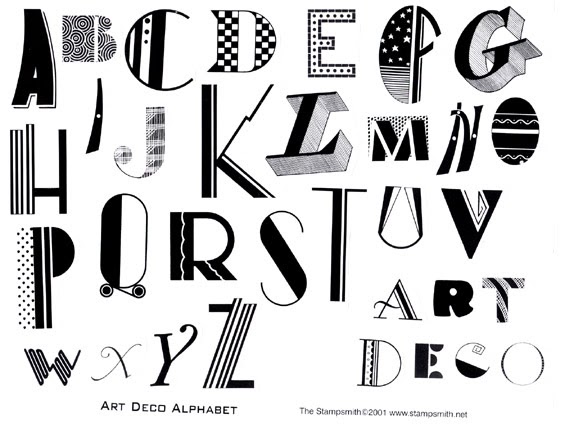
20+ лучших шрифтов в стилях ар-нуво и ар-деко (платных и бесплатных)
Ар-нуво и ар-деко — художественные направления, которые являются важной частью мировой культуры.
Их нередко путают. Но если для ар-нуво характерны плавные, “текучие” формы, то для ар-деко — геометричные четкие ломаные линии. Эти стили нашли отражение в архитектуре, изобразительном искусстве, дизайне и даже типографике.
В статье собрано более 20 как платных, так и бесплатных шрифтов в стилях ар-нуво и ар-деко. Минималистичные, элегантные, креативные, экспериментальные шрифты — вы точно найдете здесь что-то для вашего следующего проекта.
Хотите создать дизайн, неподвластный времени? Вы точно не ошибетесь, если выберете для него шрифт в стиле ар-нуво или ар-деко.
Хотя расцвет и ар-нуво, и ар-деко пришелся на 20-й век, эти стили сильно отличаются друг от друга. Ар-деко — аккуратный минималистичный, а ар-нуво — элегантный с длинными изгибами и линиями.
Эти прекрасные художественные направления прошли сквозь десятилетия и до сих пор пользуются популярностью у дизайнеров. Особенно часто к ним обращаются при работе с типографикой.
В нашей коллекции тщательно отобранных шрифтов вы точно сможете найти красивую винтажную гарнитуру, чтобы создать дизайн в викторианском стиле. Обязательно скачайте их все.
Wallington Pro — это стильный элегантный шрифт, который можно назвать идеальным примером типографики в стиле ар-нуво. Полужирные буквы с засечками, длинные изогнутые линии и оригинальный стиль — с Wallington Pro не сравнится ни один другой шрифт. Дизайн вдохновлен английской культурой конца XIX века. В набор входят 10 стилей, сотни лигатур и глифов.
Как и шрифты в стиле ар-нуво, шрифты в стиле ар-деко выглядят элегантно. Но основным отличительным признаком последних является аккуратный минималистичный внешний вид. Прекрасный пример — шрифт Decohead. Он представлен в трех различных одинаково стильных начертаниях.
Fonseca — семейство красивых шрифтов в стиле ар-деко. В набор входит 8 начертаний, а также наклонные версии каждого из них: всего 16 шрифтов. Все они выполнены в едином стиле. Гарнитура универсальна: вы можете использовать шрифты как для заголовков, так и для фрагментов текста
Bagerich — утонченный стильный шрифт. Подобные шрифты мы привыкли видеть на сайтах и в рекламных материалах таких люксовых брендов, как Gucci или Victoria’s Secret. Он состоит из букв в стиле ар-нуво, а также включает множество альтернативных глифов и лигатур, с помощью которых вы без труда сможете создавать классные логотипы, этикетки и т.
д.
Onamura — уникальный экспериментальный шрифт, который представляет собой результат смешения нескольких художественных стилей. В нем присутствуют различные элементы ар-нуво, а также готики. Благодаря этому каждая буква выглядит уникально. Шрифт идеально подходит для создания современных дизайнов, способных мгновенно привлечь внимание аудитории.
Вы можете бесплатно использовать этот деликатный минималистичный шрифт в своих личных и коммерческих проектах. Он выглядит элегантно, включает множество уникальных символов и ничем не уступает шрифтам премиум-класса.
Еще один профессиональный бесплатный шрифт в стиле ар-деко. Здесь есть все, что нужно — стилистические альтернативные глифы, поддержка нескольких языков и утонченный ретро-дизайн. Все это вы получите совершенно бесплатно.
Avenida — один из самых стильных шрифтов в нашем списке.
Хотя он вдохновлен ар-деко, в нем есть дополнительные стилистические элементы, которые придают уникальный вид каждой букве. Это отличный выбор для создания логотипов, этикеток и других элементов брендинга. Шрифт включает прописные и строчные буквы.
Перед нами высокий и узкий шрифт, состоящий исключительно из прописных букв. Fontaine — полужирный шрифт в стиле ар-деко, созданный специально для заголовков и декоративных надписей, которые должны привлекать внимание пользователей. Шрифт содержит альтернативные глифы, которые можно переключать с помощью Caps Lock.
Эти красивые женственные шрифты сочетают в себе современный облик и стиль ар-деко. Они идеально бы смотрелись на обложке журнала, а также отлично бы вписались в фирменный стиль бренда, целевой аудиторией которого являются женщины, например, косметического, и даже люксового модного бренда.
Murray — довольно простой шрифт в стиле ар-деко с тонким намеком на эстетику 20-го века.
Такая типографика элегантно смотрится на поздравительных открытках и свадебных приглашениях. Шрифт включает как прописные, так и строчные буквы.
Как называется шрифт 1920-х годов?
Самым популярным шрифтом в стиле ар-деко, выпущенным в 1920 году, был Poster Bodoni (BT) , разработанный Чонси Х. Гриффитом. Это шрифт с засечками с элегантным видом и подчеркнутыми вертикальными линиями. Однако он имеет мало общего с классической типографикой ар-деко, склонной к вытянутым символам с арочными элементами и геометрическим орнаментом.
Каким был первый шрифт в стиле ар-деко?
Движение ар-деко славится невероятной типографской вариативностью. Однако все началось с утра.